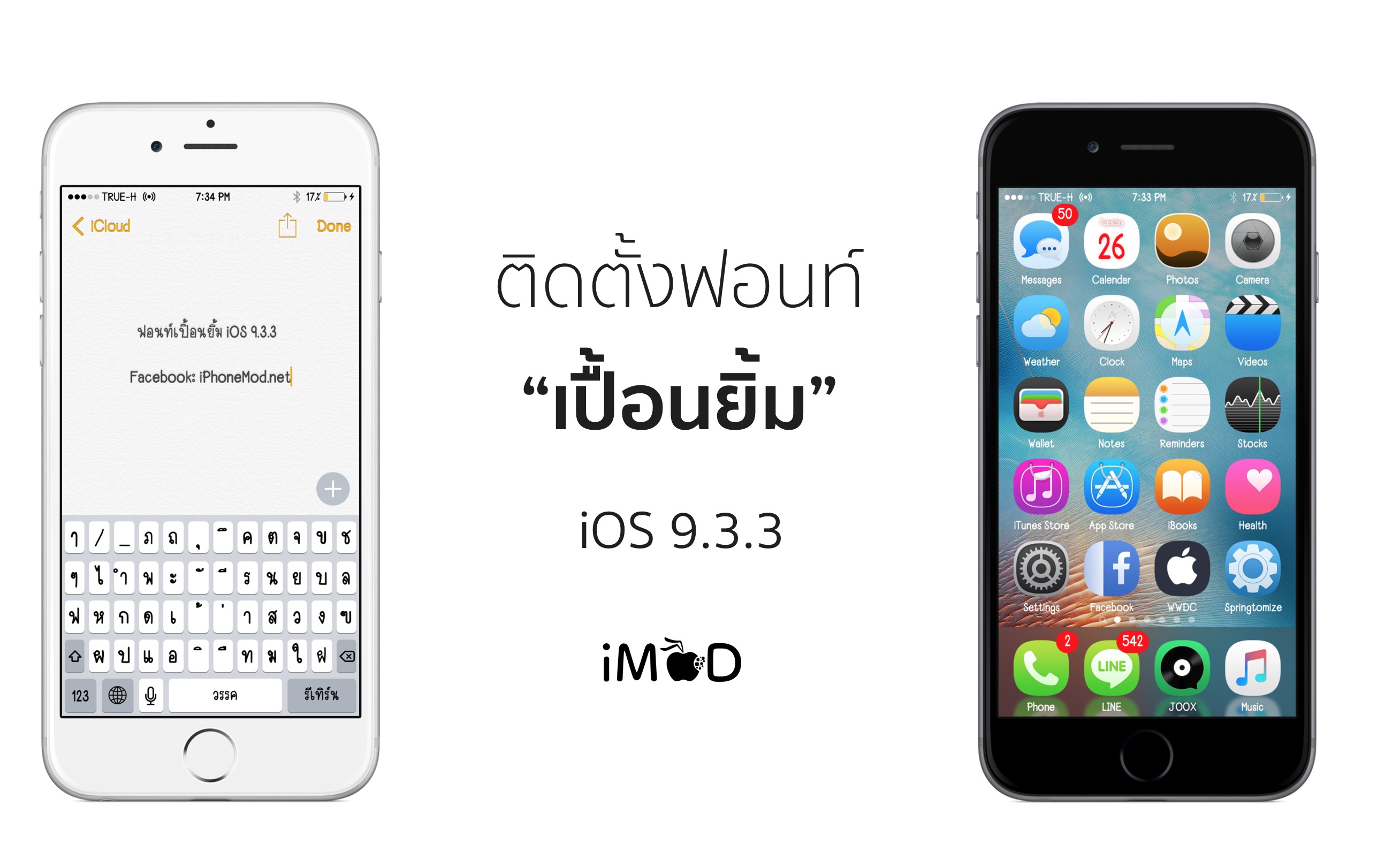
หลายคนเจลเบรคเพื่อสิ่งนี้คือ “ฟอนท์” เพื่อต้องการเปลี่ยนไปใช้ฟอนท์แบบที่น่ารักๆ บ้าง อีกหนึ่งฟอนท์ที่ได้รับความนิยมก็คือ “เปื้อนยิ้ม” ซึ่งให้ความน่ารักหลายๆ คนก็เลยอยากได้ วันนี้มินจะแนะนำวิธีการติดตั้งฟอนท์เปื้อนยิ้มเอาไว้ใช้กันนะครับ